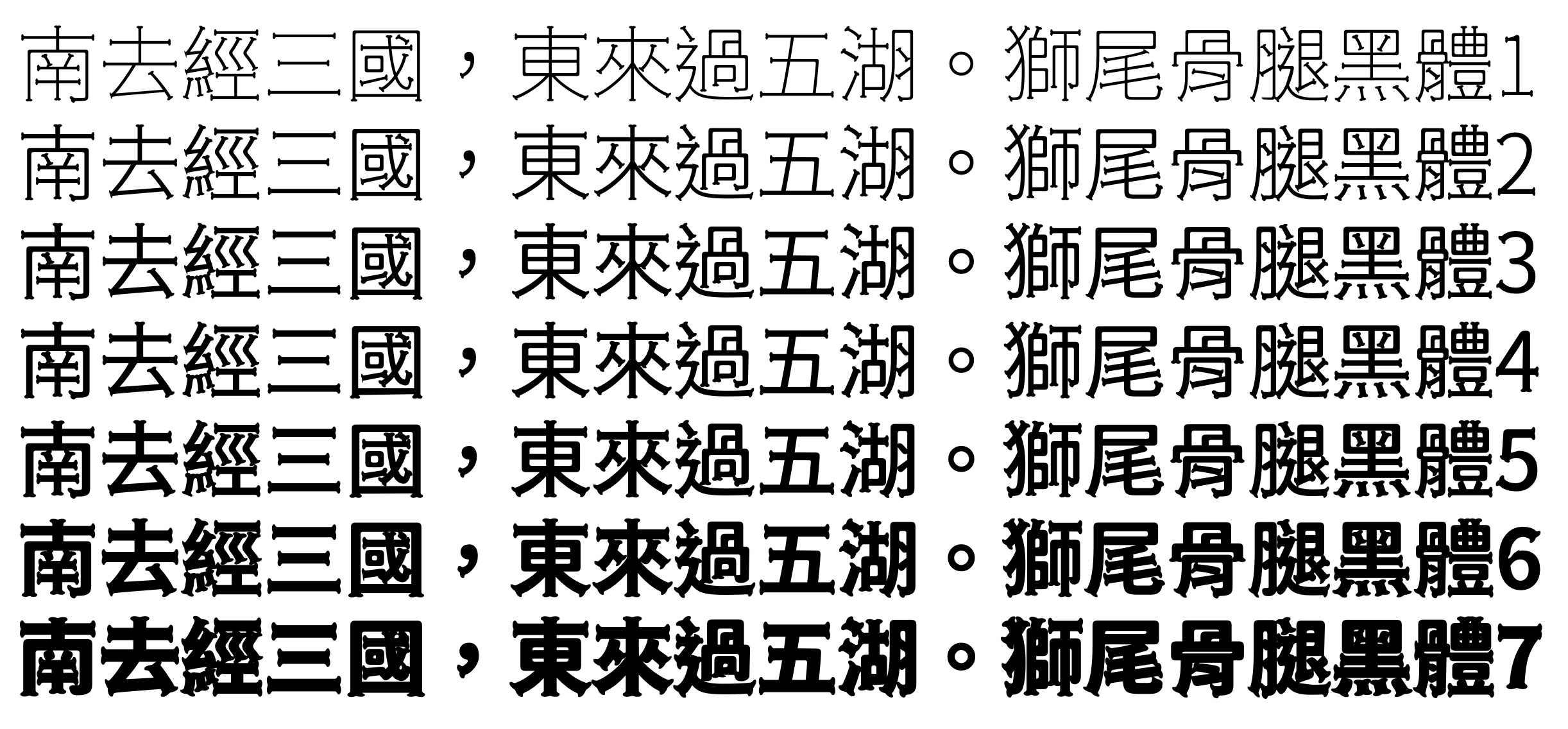
獅尾骨腿黑體
狮尾骨腿黑体基于思源黑体的笔触变骨头改造,更加简明现代化的字体。支援简体中文、繁体中文、韩文与日文;可以免费商用,欢迎大家自由应用、自由改作!
狮尾骨腿黑体的特色是:笔画的起头与收尾较宽,有骨头造型。
「狮尾骨头黑体」与「狮尾骨腿黑体」差别在有没有拔脚,「拔脚」就是会有较少的笔画,例如移除「口」字的左右下角会多出的短线条。有拔脚的字会较圆,但是会造成有些字因直接去掉腿后左右不平衡、左右不对衬的「悬空」问题。改使用「腿」系列字体就不会有这个问题。
“狮尾骨腿黑体”设计上针对笔画粗细支援7种字重,所以不论大标、小标、简单的段落排版都能清晰辨识:
附注:目前有些笔画还没有套用到效果,是程式需要改进的地方。